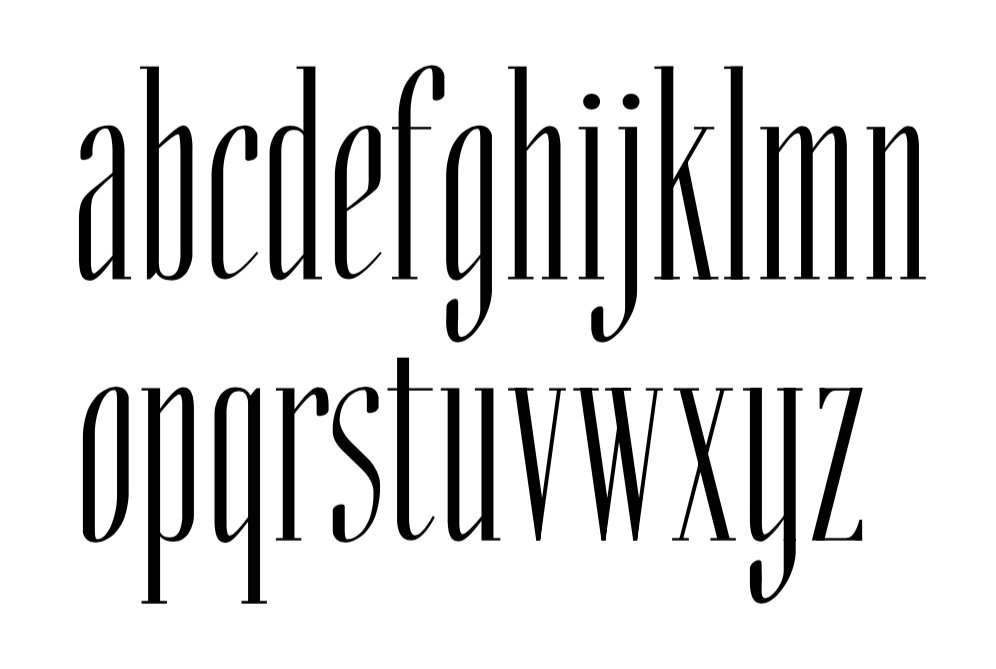
Шрифт для штампа: Образцы шрифтов для печатей
шрифт с засечками или рубленный шрифт — Фабрика печатей
Визуальный облик печати чрезвычайно важен для восприятия документа в целом и штемпеля в отдельности. Ключевую роль в этом параметре играет шрифт, ведь большая часть миниатюрного изображения, как правило, представлена текстовой составляющей. То есть для создания привлекательной печати необходимо правильно выбрать шрифт и реализовать его, но, сначала, определимся с тем, какие вариации в принципе используются сегодня:
- С засечками;
- Рубленные;
- Рукописные;
- Машинописные;
- Декоративные.
Некоторые из названий интуитивно понятны и не требуют дополнительного разъяснения, другие – наоборот. Чтобы не тратить время, рассмотрим лишь наиболее популярные современные шрифты.
Шрифт с засечками
Засечки – это небольшие поперечные линии на конце каждого переходного штриха. Также имеется четкий переход от толстой линии к более тонкой.
Классическим образцом шрифта, обильно использующего засечки, является Time New Roman, знакомый всем и каждому работающему с текстами человеку. Он превосходно смотрится на бумаге, поэтому столь часто встречается в печатных изданиях, будто книги или газеты в традиционном формате.
Однако, для штемпелей такой шрифт не является пригодным в той же мере, что и для текстовой составляющей. Основным недостатком считается их непрактичность – при отмывке печати после активного использования, засечки могут легко оторваться, так как представляют собой слабые, тонкие места. Из-за этого был переделан не один штемпель, поэтому прибегать к таким шрифтам не целесообразно.
Рубленный шрифт
Название исходит из первого визуального представления об элементах шрифта. Если засечки – это тонкие места перехода от одной толщины к другой, то в рубленых вариациях таких слабых мест просто нет. Буквы здесь единообразные, словно монолитно высечены. Чтобы лучше понять, как они выглядят, достаточно открыть любой текстовый редактор – Arial или Pragmatica к вашим услугам.
Они прекрасно отображают преимущества рубленых и шрифтов и являются оптимальным решением для электронного текста.
Тоже можно сказать и о печати. В профессиональных кругах считается хорошим тоном, когда представленный эскиз штемпеля выполнен в рубленых шрифтах. К тому же изготавливать их обычно проще, ведь россыпь заготовок у мастера уже имеется, ему достаточно лишь скомпоновать соответствующий текст и выполнить рисунок, если он имеется. Соответственно, получить готовую печать или штамп можно будет куда быстрее. Да и прослужит она дольше, чем штемпель с засечками.
Шрифты для печатей. Шрифт для печати или штампа
Большинство российских печатей (всевозможные «ОБЩЕСТВО С ОГРАНИЧЕННОЙ ОТВЕТСТВЕННОСТЬЮ» и т.д.) набраны этим шрифтом Но уже в жирном начертании этот шрифт не очень удобен, слишком толстый, поэтому многие прибегают к жирному Arial.